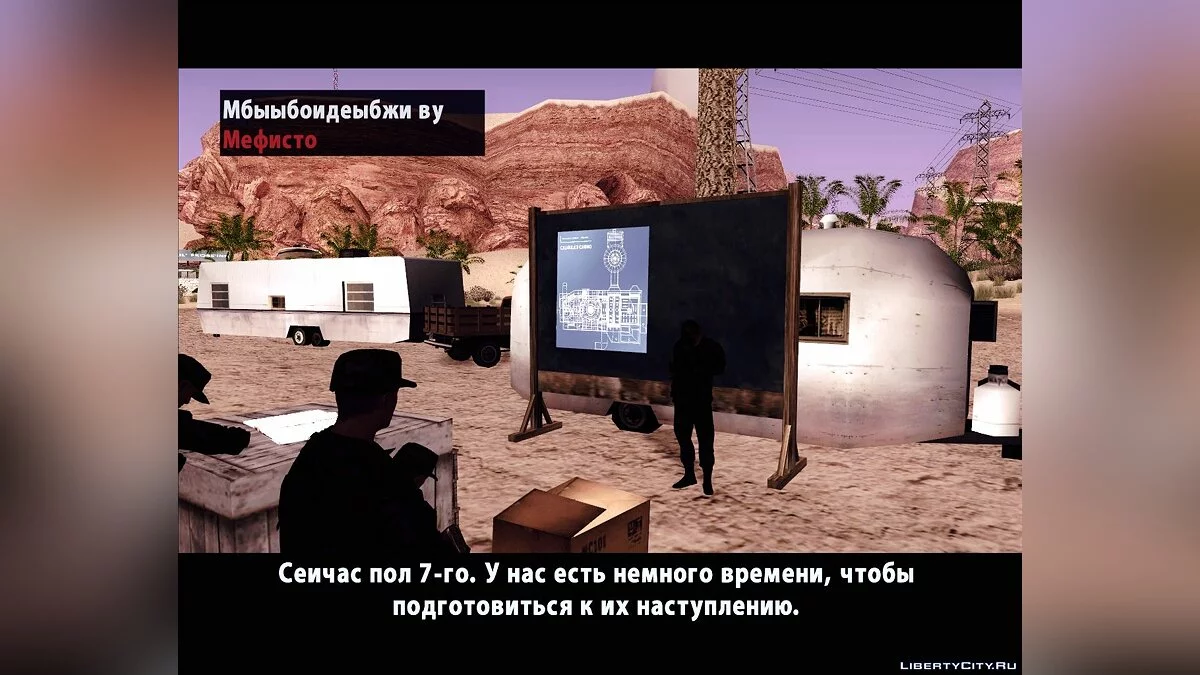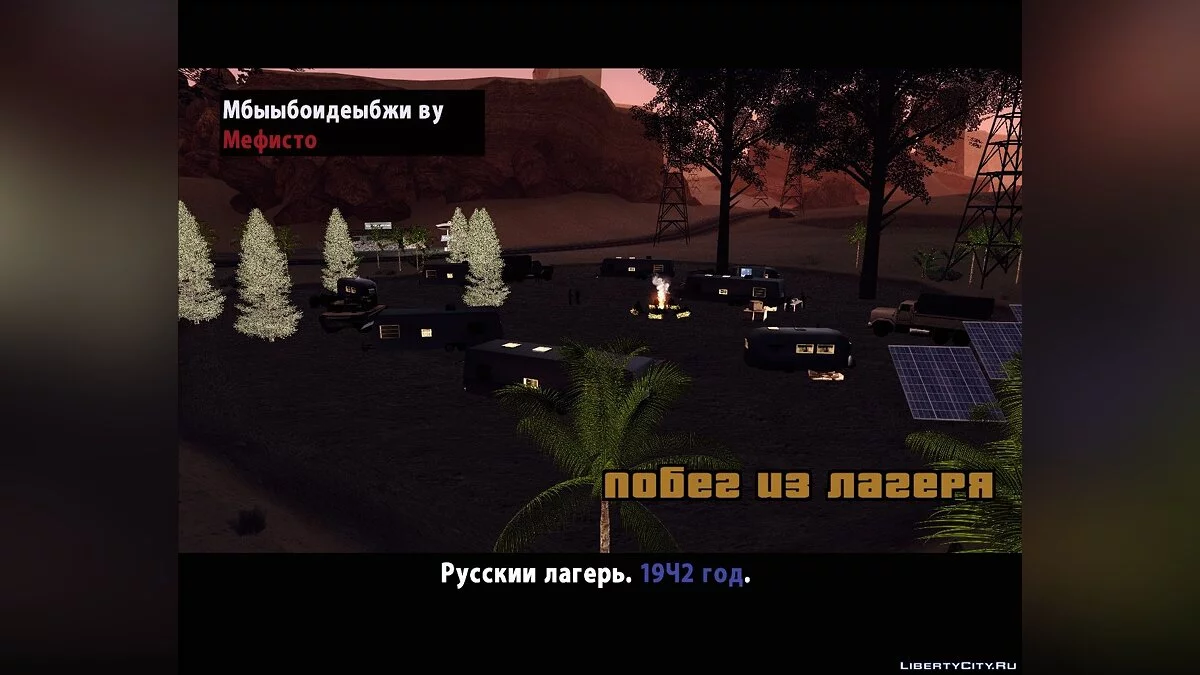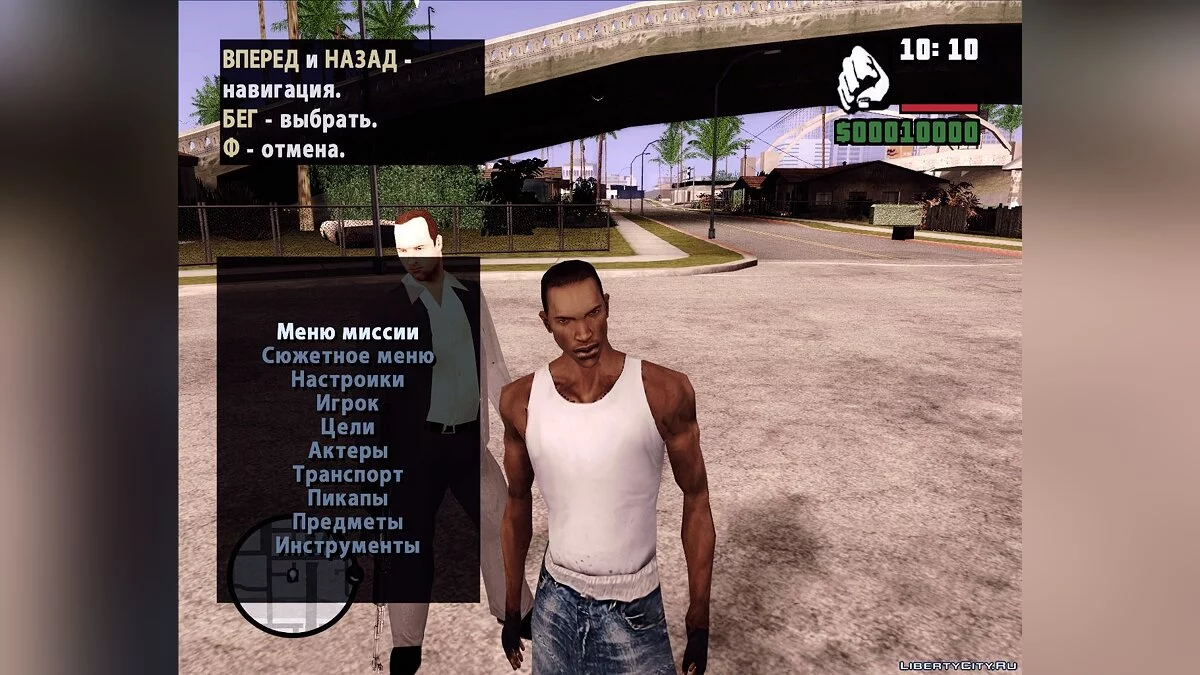
Русскоязычный шрифт для DYOM v.2 (ФІНАЛ)
ВИТРАЧЕНО - минуле століття в діомерстві!
Ось і вийшла друга версія мого, напевно, найуспішнішого мода. Що ж нового в порівнянні з попередньою версією?
1. Тепер підтримуються ЛЮБІ русифікатори для GTA SA!
Цей шрифт тепер працює як на ВИТРАЧЕНИХ русифікаторах, так і на русикі від SanLTD.
2. Новий шрифт.
Багато хто любить русифікатор GTA SA від SanLTD, тому нова версія базується на шрифті саме
цього русифікатора, а значить, не псує атмосферу гри.
3. Виправлено більшість помилок з першої версії.
Тепер у моді значно менше багів, гра більш комфортна. Але незважаючи на це, шрифт все ще підходить для використання виключно в DYOM. У самій сюжетній грі SA будуть видні баги шрифта (але вильотів немає).
Русскоязычный шрифт для DYOM v.2 (FINAL)
ПОТРАЧЕНО - прошлый век в диомерстве!
Вот и вышла вторая версия моего, наверное, самого успешного мода. Что же нового по сравнению с предыдущей версией?
1. Теперь поддерживаются ЛЮБЫЕ русификаторы для GTA SA!
Этот шрифт теперь идет как на ПОТРАЧЕННЫХ русификаторах, так и на русике от SanLTD.
2. Новый шрифт.
Многие любят русификатор GTA SA от SanLTD, поэтому новая версия основана на шрифте именно
этого русификатора, а значит, не портит атмосферу игры.
3. Пофиксено большинство ошибок из первой версии.
Теперь в моде намного меньше багов, игра более комфортна. Но не смотря на это, шрифт все равно пригоден для использования исключительно в DYOM. В самой сюжетной игре SA будут видны баги шрифта (но вылетов нет).